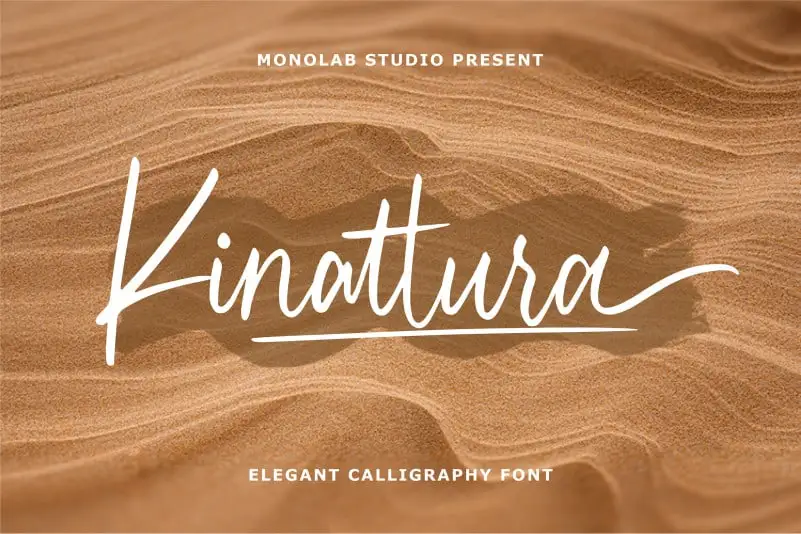
Kinattura Script Font – Fonte Grátis
Kinattura Script Font
Agradeçemos por visitar a página do Kinattura Script Font. Esta elegante fonte escrita à mão é perfeita para quem busca uma solução criativa e sofisticada para seus projetos digitais. Inspirada no estilo da calligrafia moderna, a Kinattura Script é uma opção ideal para branding, selinhos de aniversário, embalagens de produtos, convites promocionais e muito mais. Essa fonte destaca-se por sua simplicidade moderna, enquanto mantém um charme autêntico. Você receberá um conjunto completo dos caracteres minúsculos e maiúsculos, números e sinais de pontuação, além de símbolos multilíngues, incluindo suportes para letras iniciais ou finais em desenho, ligações entre letras e extras de desenhos. A Kinattura Script é uma escolha perfeita para aqueles que buscam um estilo elegante e sofisticado sem comprometer a simplicidade, tornando-a uma opção versátil e de alto padrão. Seja para um selinho de aniversário requintado ou uma embalagem de produto minimalista, a Kinattura Script atende às necessidades de cada projeto com maestria. Não hesite em explorar mais sobre esta fonte que transforma textos digitais em obras de arte elegantes.